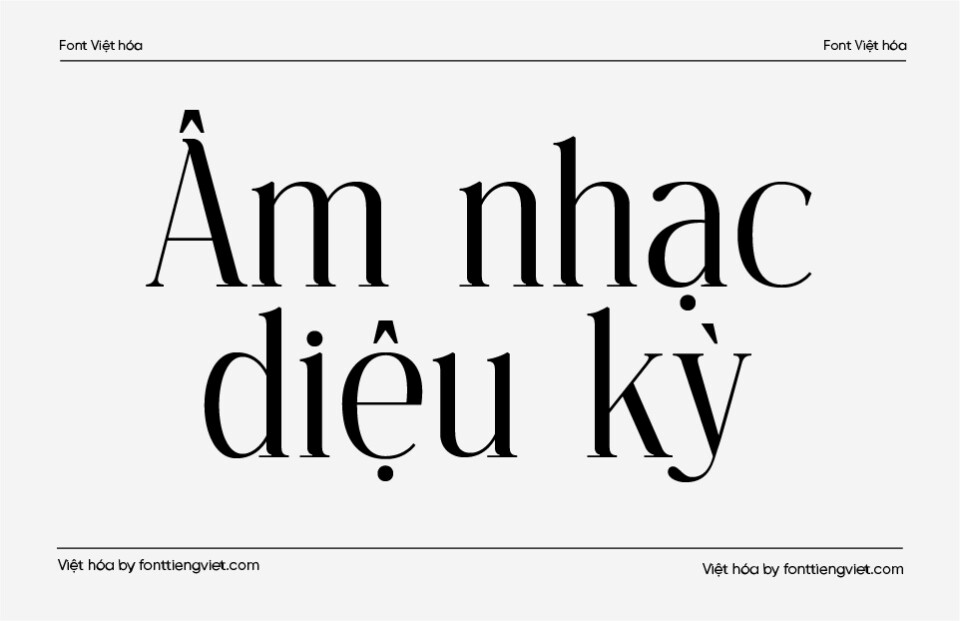
Tải Ngay Bộ Font Việt hóa 1FTV VIP Netyrac Đẳng Cấp Cho Thiết Kế Đồ Họa Giới thiệu về bộ Font Việt hóa 1FTV VIP Netyrac trong thiết kế hiện đạiTrong thế giới sáng tạo nội dung hiện nay, việc lựa chọn một phông chữ phù hợp đóng vai trò quyết định đến sự thành công của một tác phẩm nghệ thuật. Bộ Font Việt hóa 1FTV VIP Netyrac nổi lên như một hiện tượng trong cộng đồng thiết kế nhờ sự kết hợp hoàn hảo giữa nét hiện đại và tính ứng dụng cao. Nếu bạn đang tìm kiếm một công cụ để nâng tầm hình ảnh, thì đây chính là lựa chọn không thể bỏ qua. Đặc biệt, đối với những người làm nghề tại Việt Nam, việc sở hữu các bộ Font Miễn Phí đã được tối ưu tiếng Việt giúp tiết kiệm rất nhiều thời gian và công sức trong quá trình làm việc.Đặc điểm nổi bật của Font Việt hóa 1FTV VIP NetyracPhong cách thiết kế độc đáo và linh hoạtFont Việt hóa 1FTV VIP Netyrac mang trong mình một cấu trúc hình học chuẩn xác nhưng không kém phần mềm mại. Các đường nét được gọt giũa tỉ mỉ, giúp bộ font này có thể thích nghi tốt trên cả nền tảng kỹ thuật số lẫn in ấn truyền thống. Với độ dày nét đa dạng, từ mỏng nhẹ đến đậm chắc, người dùng có thể dễ dàng tạo ra sự tương phản cần thiết cho các tiêu đề lớn hay các đoạn văn bản dài mà vẫn đảm bảo được tính thẩm mỹ tổng thể. Đây là công cụ đắc lực cho các bạn học sinh và sinh viên khi thực hiện các dự án thuyết trình tại nhà trường.Khả năng hiển thị tiếng Việt hoàn hảoMột trong những ưu điểm lớn nhất của Font Việt hóa 1FTV VIP Netyrac chính là bộ dấu tiếng Việt được chăm chút kỹ lưỡng. Thông thường, nhiều font ngoại nhập khi về Việt Nam thường gặp lỗi hiển thị các ký tự đặc biệt như “ơ”, “ư”, “đ” hoặc dấu ngã, dấu hỏi bị lệch vị trí. Tuy nhiên, với phiên bản VIP Netyrac này, mọi vấn đề về hiển thị đều được giải quyết triệt để. Các dấu thanh được đặt ở vị trí khoa học, giúp văn bản trở nên chuyên nghiệp và dễ đọc hơn bao giờ hết, đáp ứng tiêu chuẩn khắt khe của các nhà thiết kế đồ họa chuyên nghiệp.Ứng dụng thực tiễn của Font Việt hóa 1FTV VIP Netyrac trong đời sốngNhờ vào vẻ ngoài sang trọng và hiện đại, bộ font này thường xuyên được sử dụng trong các chiến dịch marketing, thiết kế logo và bộ nhận diện thương hiệu. Trong môi trường giáo dục, thầy cô và học sinh có thể dùng nó để trang trí báo tường, làm thiệp chúc mừng hoặc trình bày các tiểu luận chuyên môn. Khả năng đọc hiểu tốt của nó giúp người xem không bị mỏi mắt, đồng thời tạo ra cảm giác tin cậy và hiện đại cho nội dung được truyền tải. Sự linh hoạt này giúp Font Việt hóa 1FTV VIP Netyrac trở thành người bạn đồng hành tin cậy cho mọi dự án sáng tạo từ đơn giản đến phức tạp.Kết luận và hướng dẫn tải fontTóm lại, việc sử dụng các phông chữ chất lượng như Font Việt hóa 1FTV VIP Netyrac sẽ giúp bạn tự tin hơn trong việc thể hiện ý tưởng cá nhân. Sự tinh tế trong từng nét chữ không chỉ làm đẹp thêm cho tác phẩm mà còn khẳng định sự chuyên nghiệp của người thiết kế. Hãy luôn cập nhật những xu hướng mới nhất để không bị tụt hậu trong dòng chảy sáng tạo. Bạn có thể dễ dàng tìm kiếm và tải về bộ Font Miễn Phí, Font Việt Hóa, Font Việt hóa 1FTV VIP Netyrac để bắt đầu hành trình thiết kế của mình ngay hôm nay. Hy vọng rằng bộ công cụ này sẽ mang lại cảm hứng bất tận cho các dự án sắp tới của bạn.
Font Việt hóa 1FTV VIP Netyrac